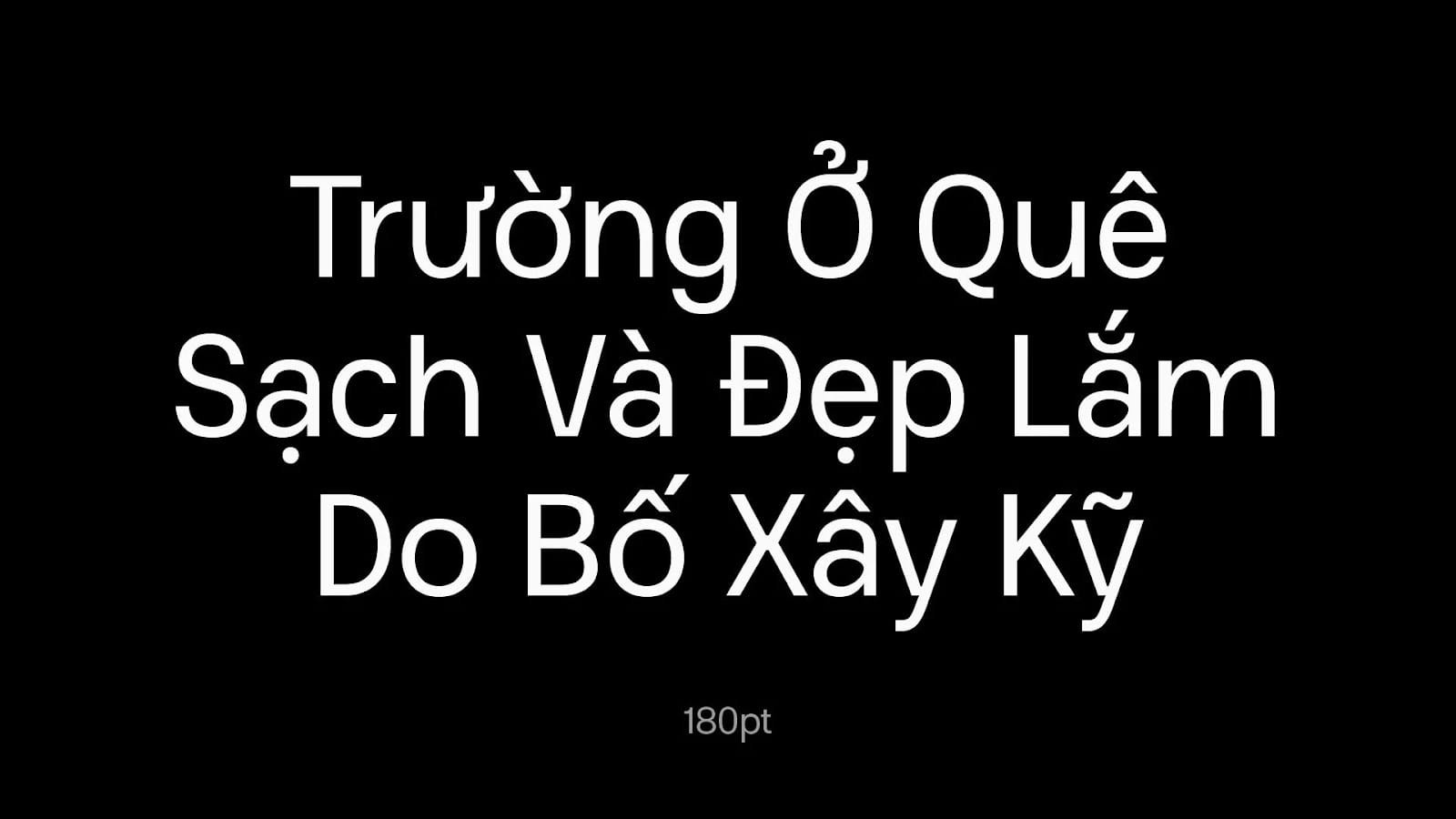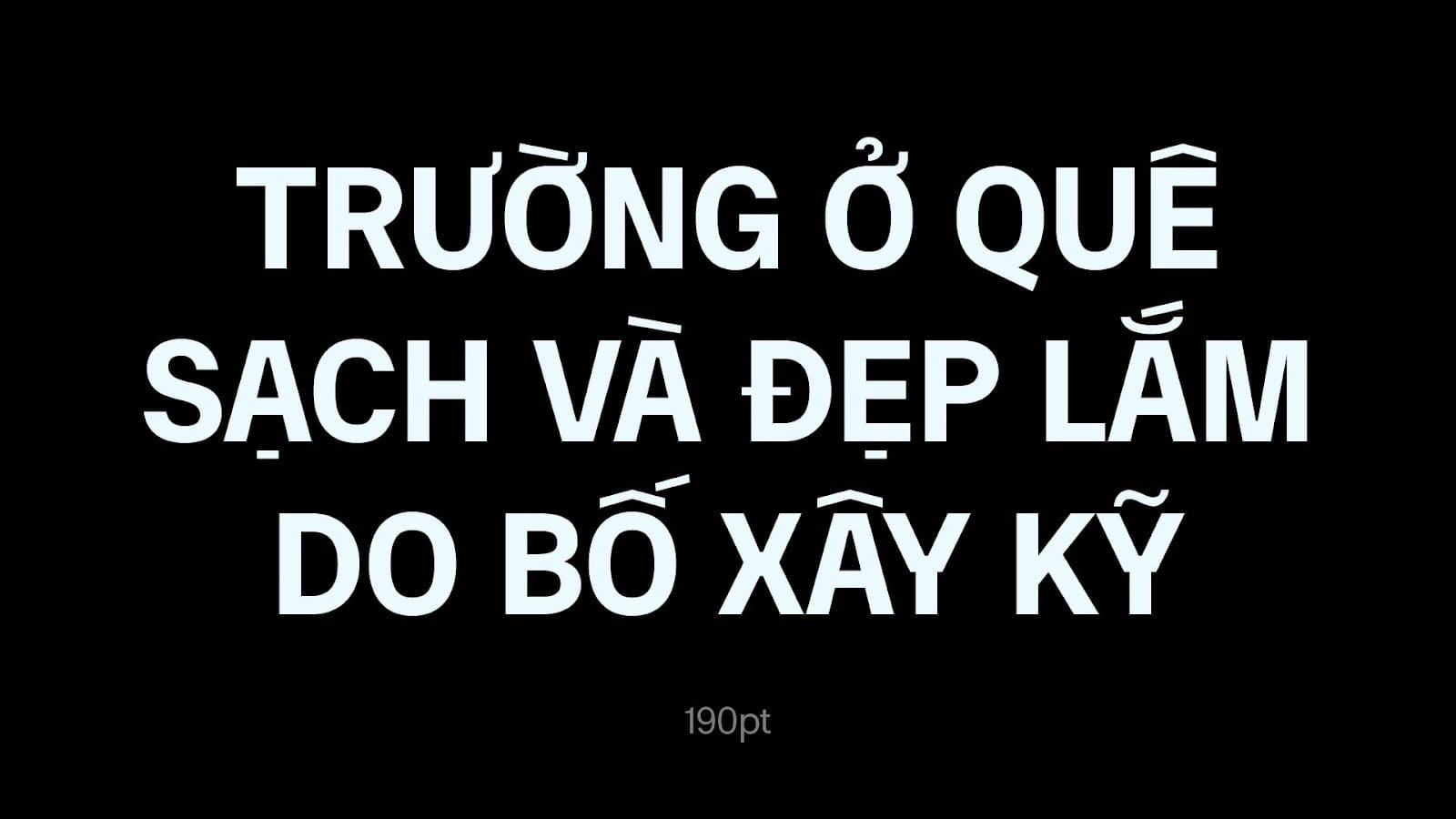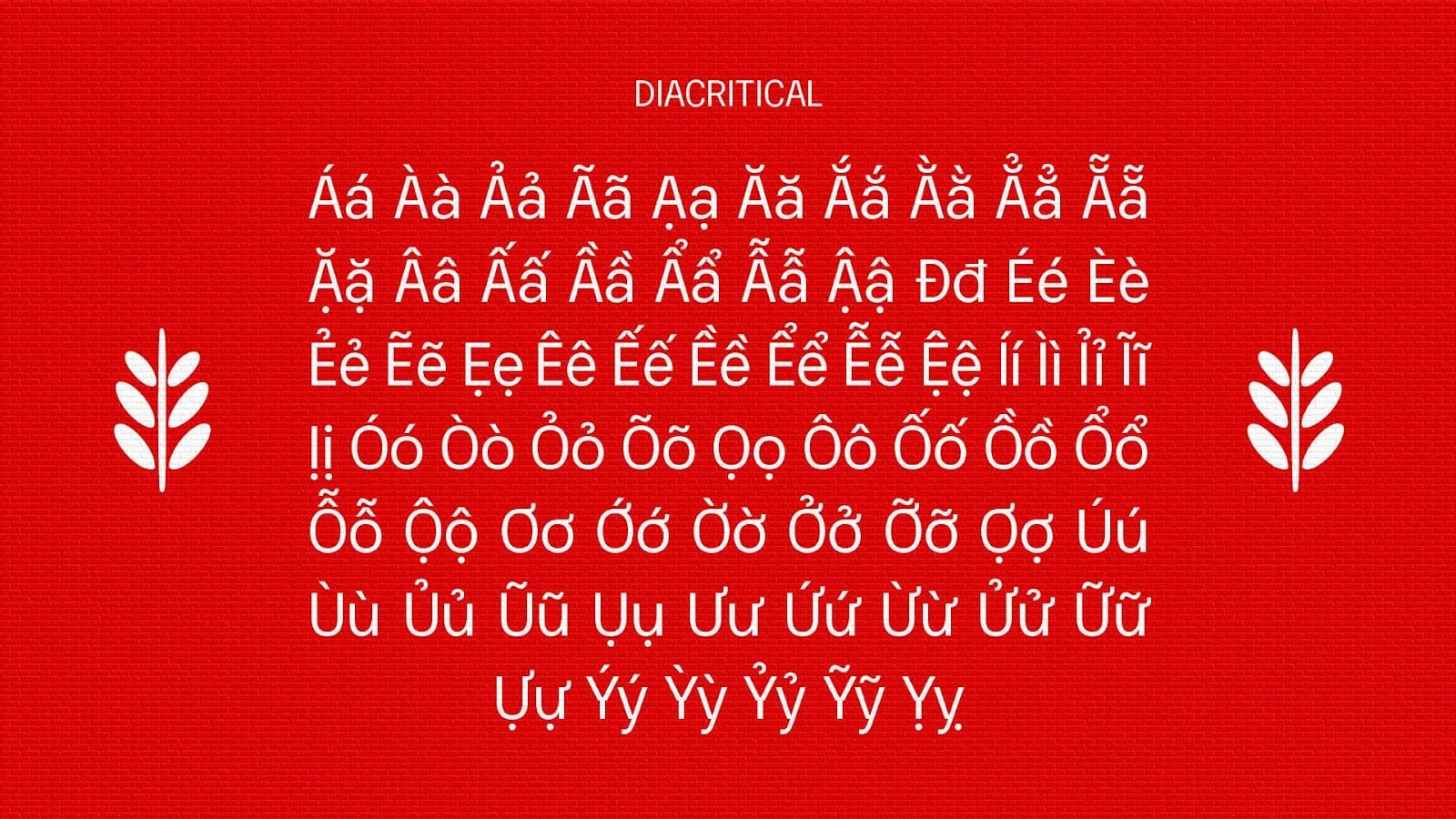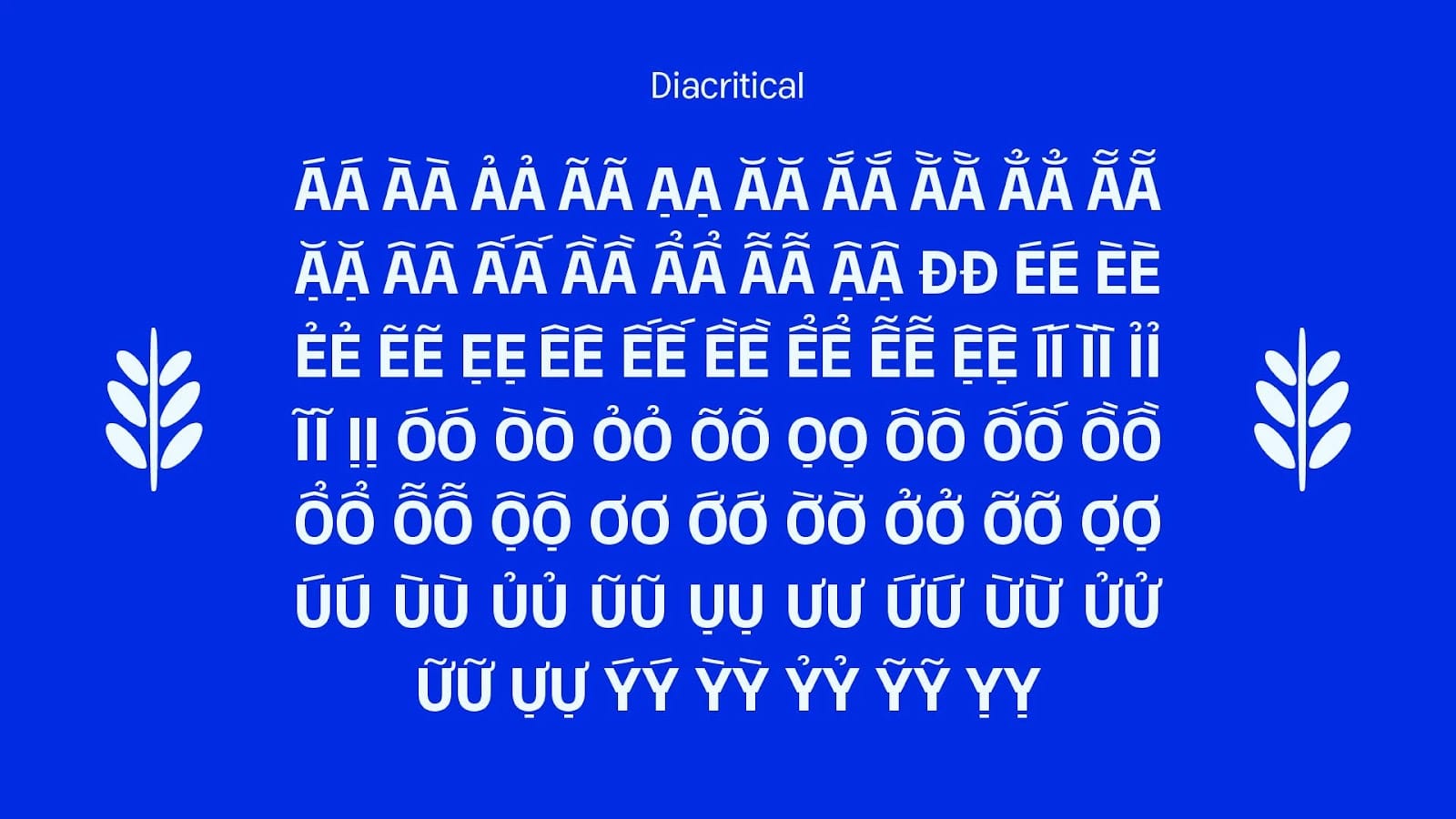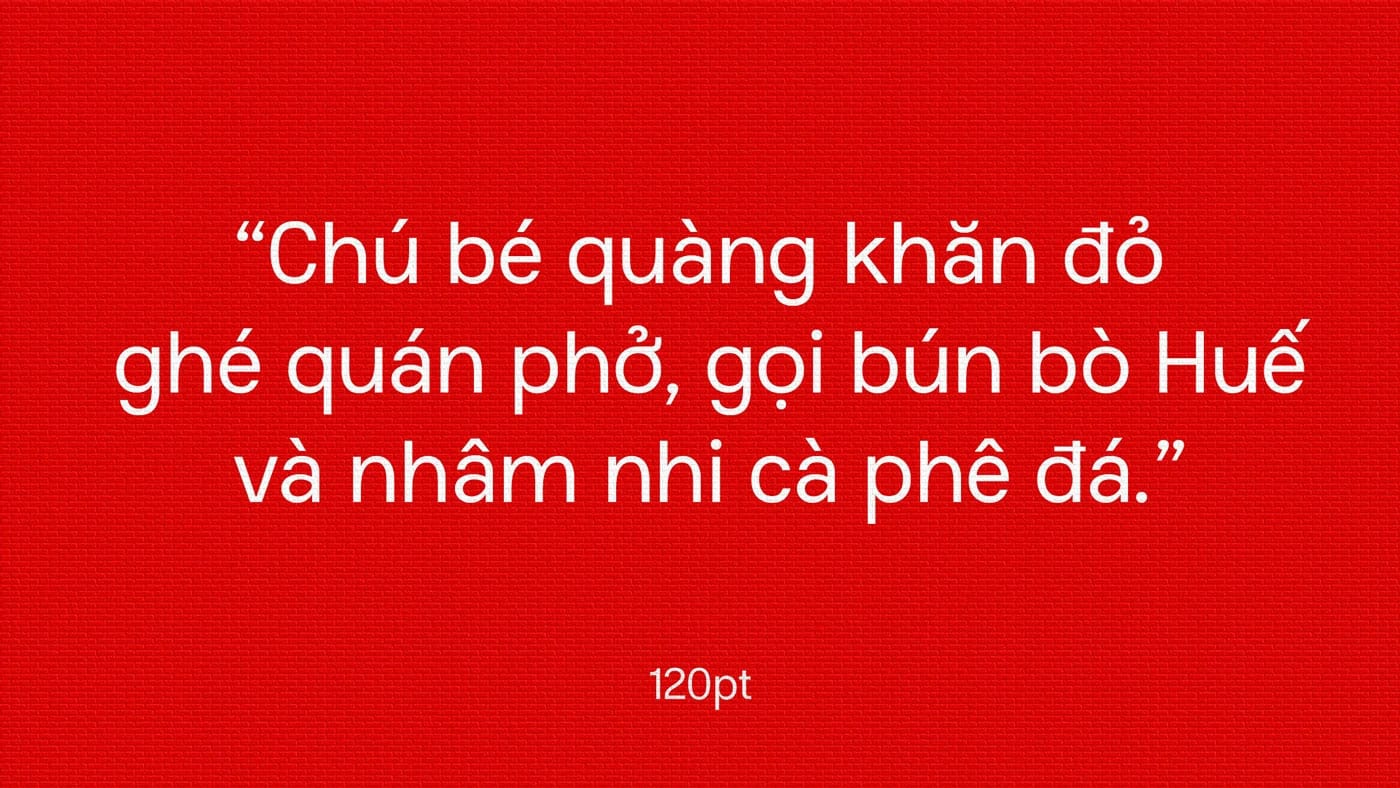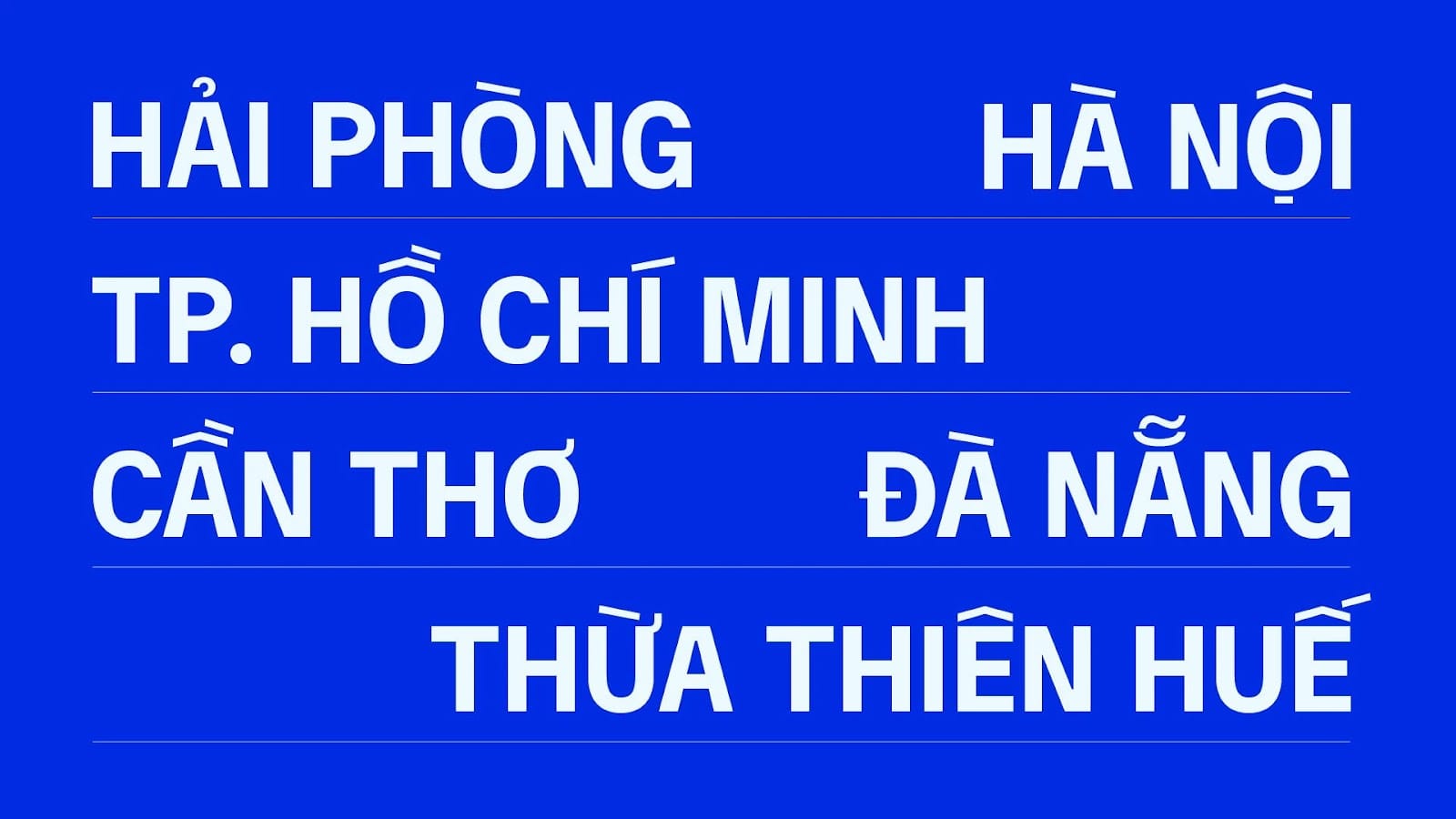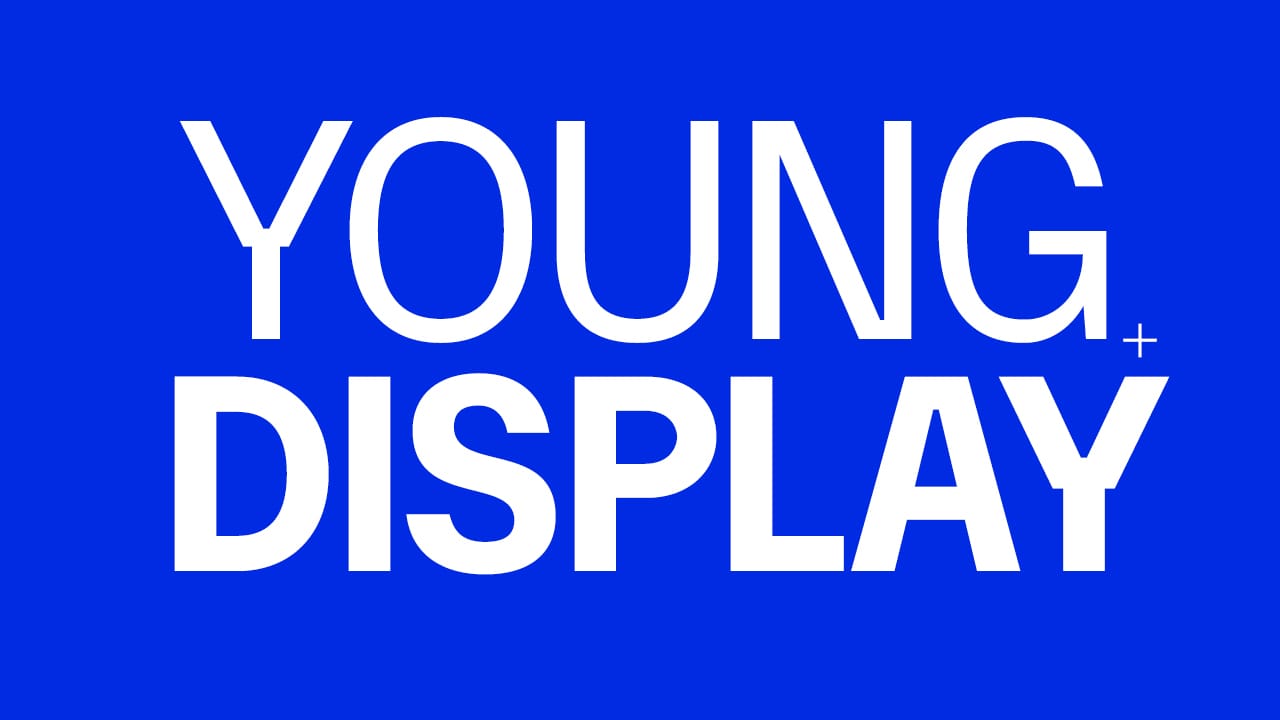
Young Typeface là sans-serif neo-grotesque hiện đại được thiết kế bởi PHƯỚC SANG, mang tinh thần tối giản, trẻ trung và dễ ứng dụng. Lấy cảm hứng từ font Space Grotesk, Young sở hữu cấu trúc gọn gàng, đường nét mềm mại và khả năng đọc tốt, phù hợp cho branding, editorial, digital design và các dự án truyền thông hiện đại.
Bên cạnh phiên bản Young, font chữ còn được phát triển thêm phiên bản Young – Bold Display. Phiên bản Display mang sắc thái mạnh mẽ hơn, đậm nét hơn và giàu cá tính hơn, đặc biệt phù hợp cho headline, poster, logo và visual identity.
Một điểm nổi bật của Young là sự chú trọng đến hệ thống dấu tiếng Việt. Ở phiên bản Display, phần dấu được lấy cảm hứng từ Phudu và Vinamilk, giúp bộ chữ vừa giữ được tính hiện đại, vừa có bản sắc riêng trong ngữ cảnh thiết kế Việt Nam.